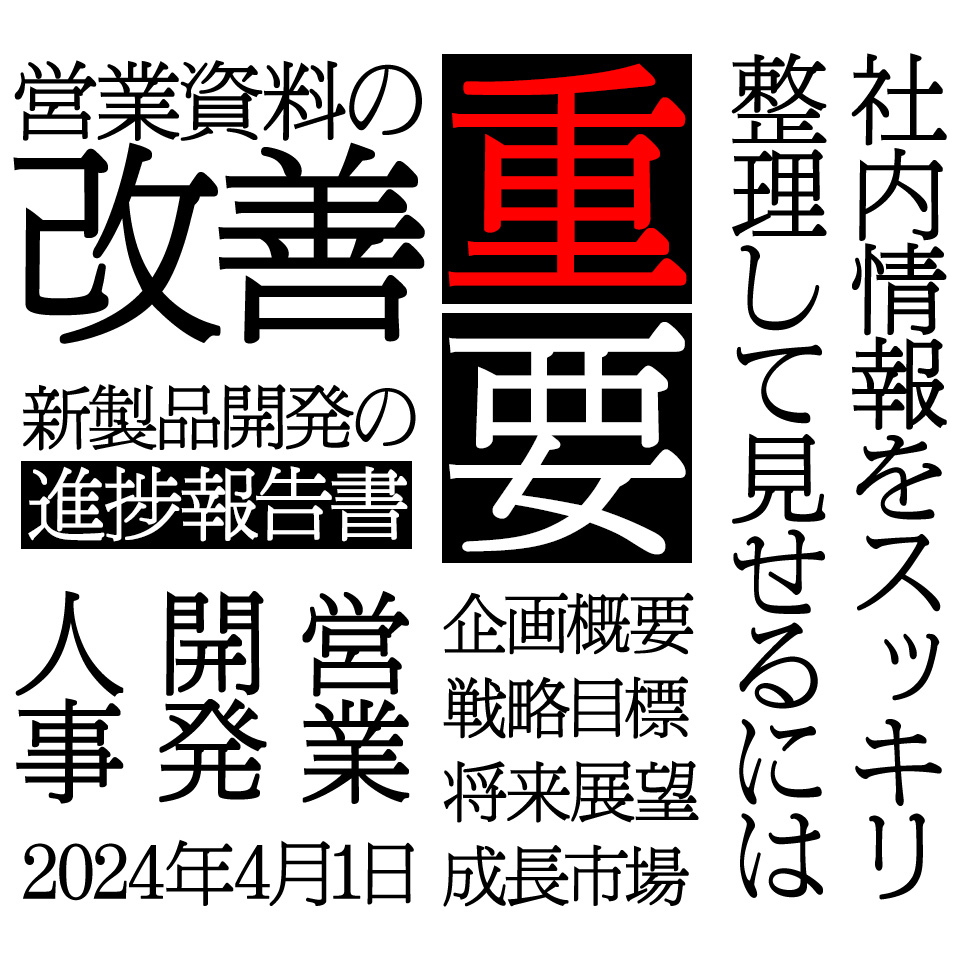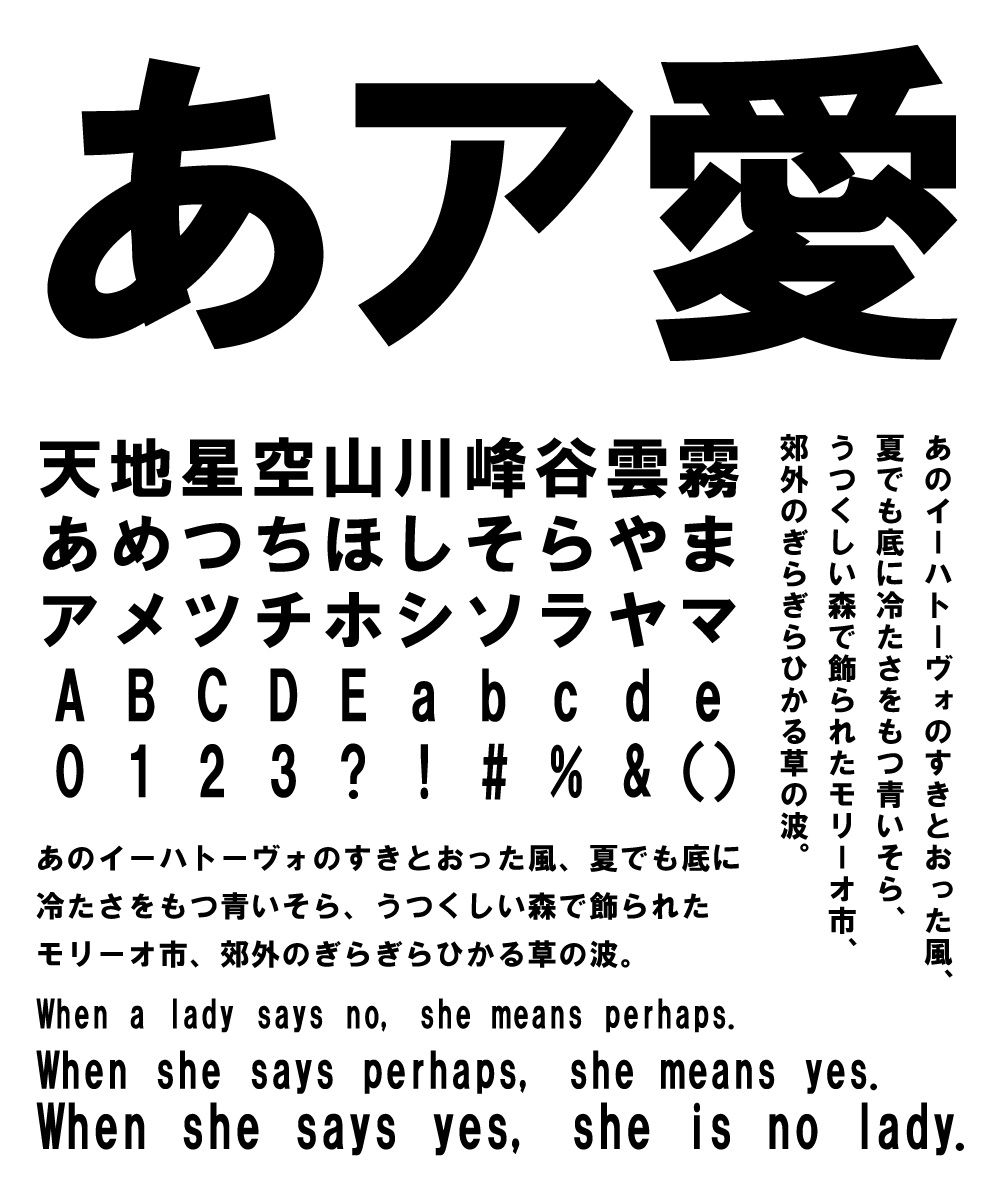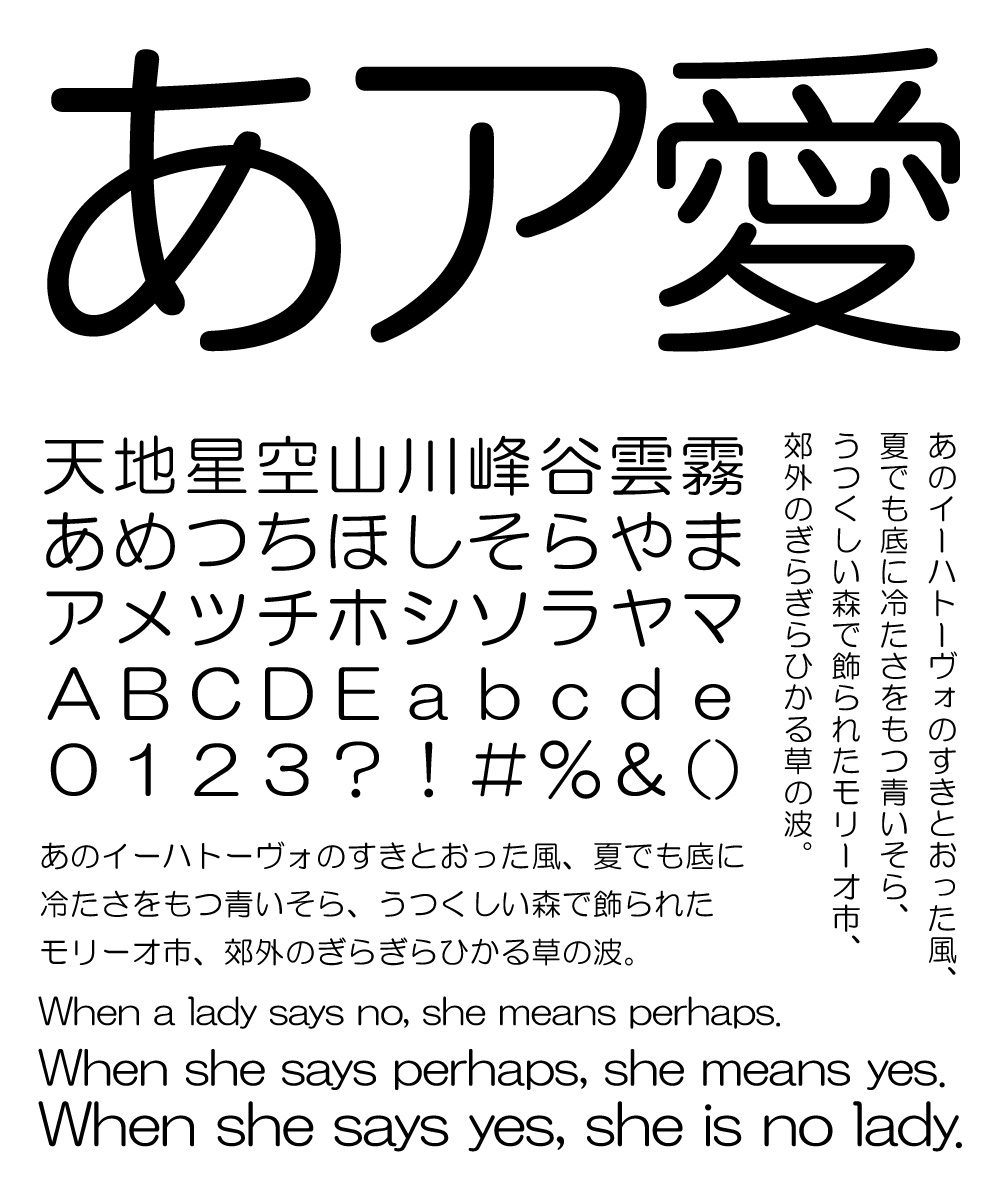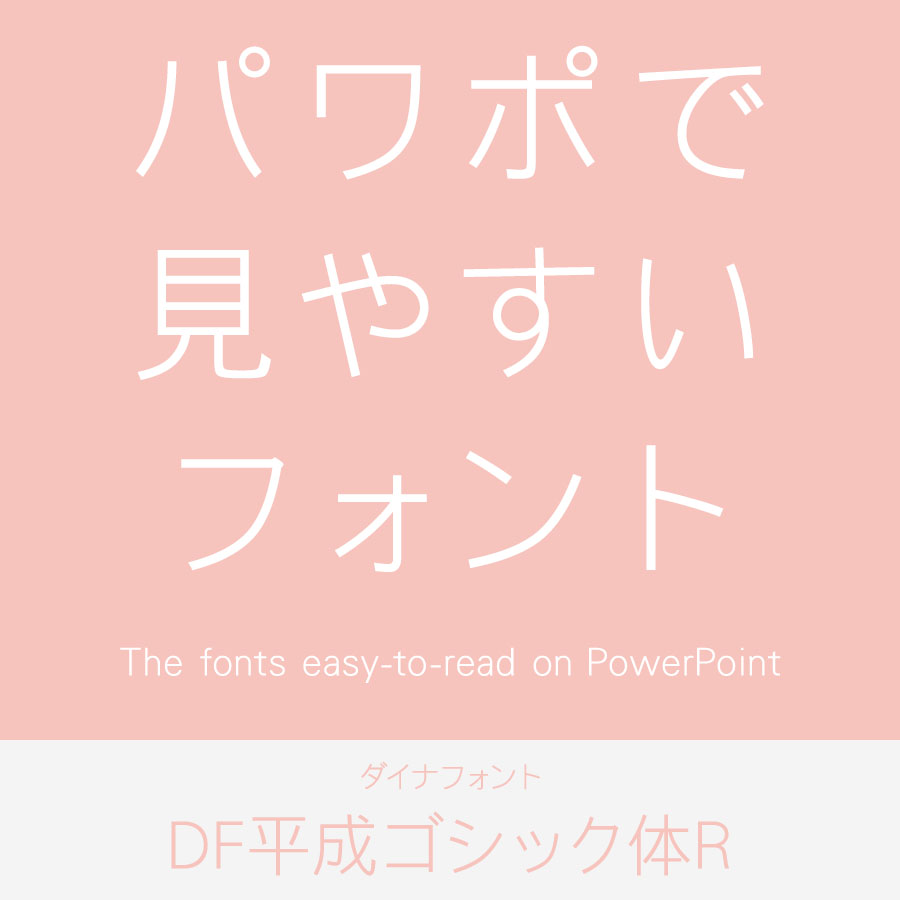
プレゼン資料の成功は、視覚的な要素に大きく影響されます。特に本文のフォント選びは、情報の伝達効率と読者の印象に直結します。明朝体、ゴシック体、毛筆書体、手書きフォントの四つのフォントタイプを取り上げ、それぞれの特性や適用場面、メリット、デメリットを解説し、最適なフォント選びなどをご紹介します。
パワーポイントのフォント選びの5つのポイント
プレゼン資料に適したフォントを選ぶ際に考慮すべきポイントは次の5つです。
① 視認性
視認性は、フォントがどれだけ目立つか、または視覚的にどれだけ鮮明かを示します。視認性が高いフォントは、視覚的に強く、一目で理解できます。
② 可読性
可読性は、テキストがどれだけ読みやすいかを示します。可読性が高いフォントは、長時間の読み物に適しています。
③ 判読性
判読性は、文字や単語がどれだけ明確に識別できるかを示します。判読性が高いフォントは、小さなサイズでもはっきりと読むことができます。
④ 互換性
互換性は、フォントがさまざまなデバイスやオペレーティングシステムでどれだけ一貫性を保つかを示します。互換性が高いフォントは、どのデバイスでも同じように表示されます。
⑤ 太字にも対応しているか
太字のフォントは、強調したい部分に使用します。しかし、すべてのフォントが太字に対応しているわけではありません。そのため、太字を使用する予定がある場合は、太字に対応しているフォントを選ぶことが重要です。
フォントの変更だけで印象が大きく変わる
フォントの選択は、文章やプレゼンテーションの印象を根本から変える力を持っています。この記事では、フォントが視覚的なコミュニケーションにどれほど影響を与えるかを詳しく解説し、適切なフォントを選ぶための具体的なアドバイスと例を紹介します。フォントの微妙な違いが持つ意味と重要性を探ります。
パターン1:保育園・幼稚園の「おたより」編
パターン2:社内での「会議プレゼンテーション」編
プレゼンテーションは、その資料の第一印象が成功の鍵を握る場合が多いです。表紙は特に重要で、使用するフォントによって、受け手の印象が大きく変わることがあります。ここでは、プレゼン資料の表紙に適したフォントの種類を紹介し、それぞれのフォントが視聴者に与える印象やメリット、デメリットを掘り下げます。
タイプフェイス別 表紙イメージ
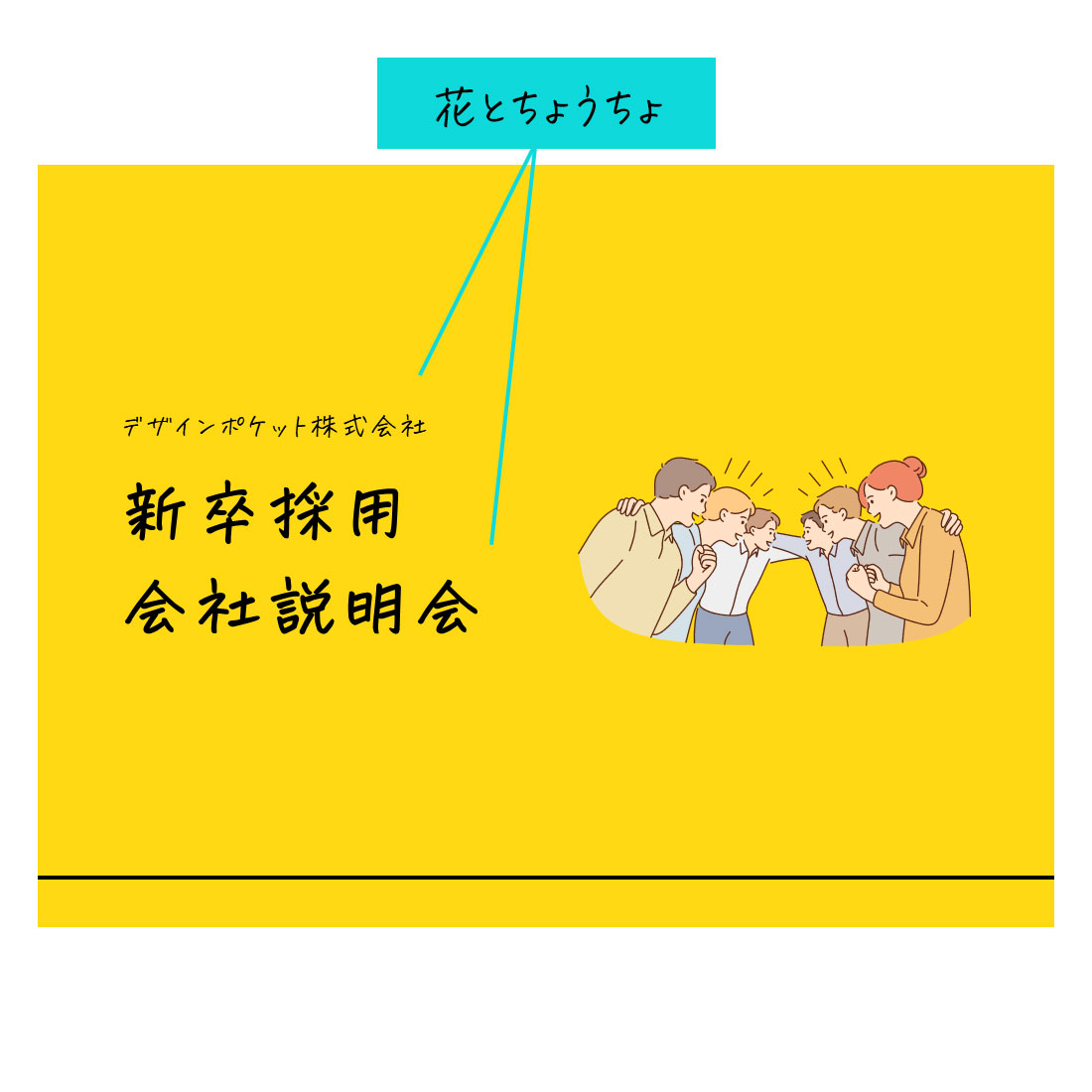
明朝体:伝統と信頼の象徴
明朝体は、その繊細なラインと伝統的な美しさで、フォーマルな印象を与えるフォントです。表紙に明朝体を使用することで、内容の正確性や信頼性を強調し、学術的または歴史的なテーマに最適です。
ゴシック体:クリアで現代的な感覚
ゴシック体は、そのクリアでモダンな外観が、特にビジネスやテクノロジー関連のプレゼンに適しています。表紙にゴシック体を使用することで、シャープでプロフェッショナルな印象を与えることができます。
毛筆書体:芸術性と感情の表現
毛筆書体は、感情豊かな表現が可能で、特に文化的または芸術的なテーマのプレゼンにマッチします。このタイプのフォントは、視聴者に強い印象を与え、情緒的なつながりを生み出すことができます。
手書き書体:カジュアルで親しみやすい
手書きフォントは、カジュアルで親しみやすい印象を与え、非公式な会議や創造的なプレゼンに適しています。この種のフォントは、個性を出しやすく、リラックスした雰囲気を作り出すことができます。
明朝体 | ・伝統的な印象で、内容の信頼性を高める ・フォーマルなプレゼンに適している |
・クリエイティブなテーマにはあまり向かない ・若い観衆には堅苦しく感じられる可能性 |
ゴシック体 | ・現代的で洗練された印象 ・視認性が高く、情報がはっきりと伝わる |
・個性を強く出すのが難しい ・過度にシンプルになりがちで印象に残りにくい |
毛筆書体 | ・強い個性と芸術的な印象を表現 ・情緒的なコネクションを促進 |
・視認性が低くなることがある ・フォーマルな設定には不向き |
手書き書体 | ・親しみやすくカジュアルな印象 ・創造性と個性を強調 |
・プロフェッショナルな印象に欠ける場合がある |
タイプフェイス別 本文
プレゼン資料の本文用フォントは、情報の伝達効率と視覚的魅力のバランスを考える必要があります。
明朝体:細部まで繊細に
明朝体は、細かい部分が特徴的で、読みやすさとフォーマル感を提供します。本文に使うことで、伝統的かつ権威のある印象を与え、特に文書や学術的な内容に適しています。
ゴシック体:現代的でクリーン
ゴシック体は明確で読みやすく、現代的なデザインに最適です。ビジネスや技術的なプレゼン資料の本文に使用することで、プロフェッショナルで洗練された印象を与えます。
毛筆書体:情緒的で芸術的
毛筆書体は、感情的なニュアンスを表現でき、文化的またはアート関連のプレゼンに適しています。ただし、本文全体に使用すると読みづらくなることがあるため、使用する際は工夫が必要です。
手書きフォント:個性的でフレンドリー
手書きフォントは、カジュアルでフレンドリーな印象を与え、創造的なプレゼンに最適です。ただし、プロフェッショナルな環境では適さない場合があります。
明朝体 | ・高い読みやすさ ・伝統的で信頼性のある印象 |
・クリエイティブな内容には少々堅苦しい ・モダンなデザインとは馴染みにくい場合がある |
ゴシック体 | ・視認性が高い ・現代的でスタイリッシュな見た目 |
・表現の幅が限られることがある ・暖かみや柔らかさを欠くことがある |
毛筆書体 | ・個性的で感情的な表現が可能 ・芸術的なデザインにマッチ |
・一般的な読みやすさに欠ける ・フォーマルな環境には不適切 |
手書き書体 | ・創造性を強調しやすい ・親しみやすい印象を与える |
・プロフェッショナルな印象に欠ける場合がある ・一部の観客には不適切と感じられることがある |
プレゼンを作る時に最適なタイプフェイスとは
プレゼン資料を作成する際には、各部分に適したフォントの選択が重要です。以下に、タイトル、見出し、本文それぞれに適したフォントの種類をご紹介します。
タイトルに最適なタイプフェイスは、ゴシック体 or デザイン・手書き書体
タイトルはプレゼンテーションの主題を伝え、視聴者の注意を引く必要があるので、ゴシック体が適しています。ゴシック体は太い線やシンプルな形状が特徴で、強い印象を与えます。ゴシック体以外にも、大胆で視覚的に魅力的なデザイン書体や手書き書体も適しています。ただし、可読性を確保するためには、複雑すぎないデザインを選ぶことが重要なポイントです。
見出しに最適なタイプフェイスは、明朝体 or ゴシック体 or デザイン・手書き書体
見出しは文章の区切りや重要なポイントを示すため、明朝体やゴシック体が適しています。明朝体は伝統的で格式のある印象を与えますが、ゴシック体は現代的でシンプルな印象を与えます。使用するフォントは、プレゼンのテーマや目的によって選択します。
本文に最適なタイプフェイスは、明朝体 or ゴシック体
本文は読みやすさが重要なので、明朝体やゴシック体が適しています。明朝体は日本語に親しみやすく、伝統的な印象を与えます。一方、ゴシック体はシンプルでモダンな印象を与えます。本文のフォントは、読み手のニーズや文書のテーマに合わせて選択します。
2種類から3種類のフォントを使用すると綺麗な仕上がりに!
パワーポイントでプレゼンテーション資料を作成する際のフォント選択については、特定の制限数はありません。しかし、デザインの観点から言えば、一般的には2種類から3種類のフォントを使用することが推奨されます。
これは視覚的な一貫性を保つためで、多くのフォントを使用すると視覚的な混乱を引き起こし、メッセージの伝達を困難にする可能性があります。一方、フォントが1種類だけでは、強調したいポイントを視覚的に区別するのが難しくなるかもしれませんので、最大のフォント数は3種類が一般的なガイドラインとなります。
2種類から3種類のフォントを使ってみました。
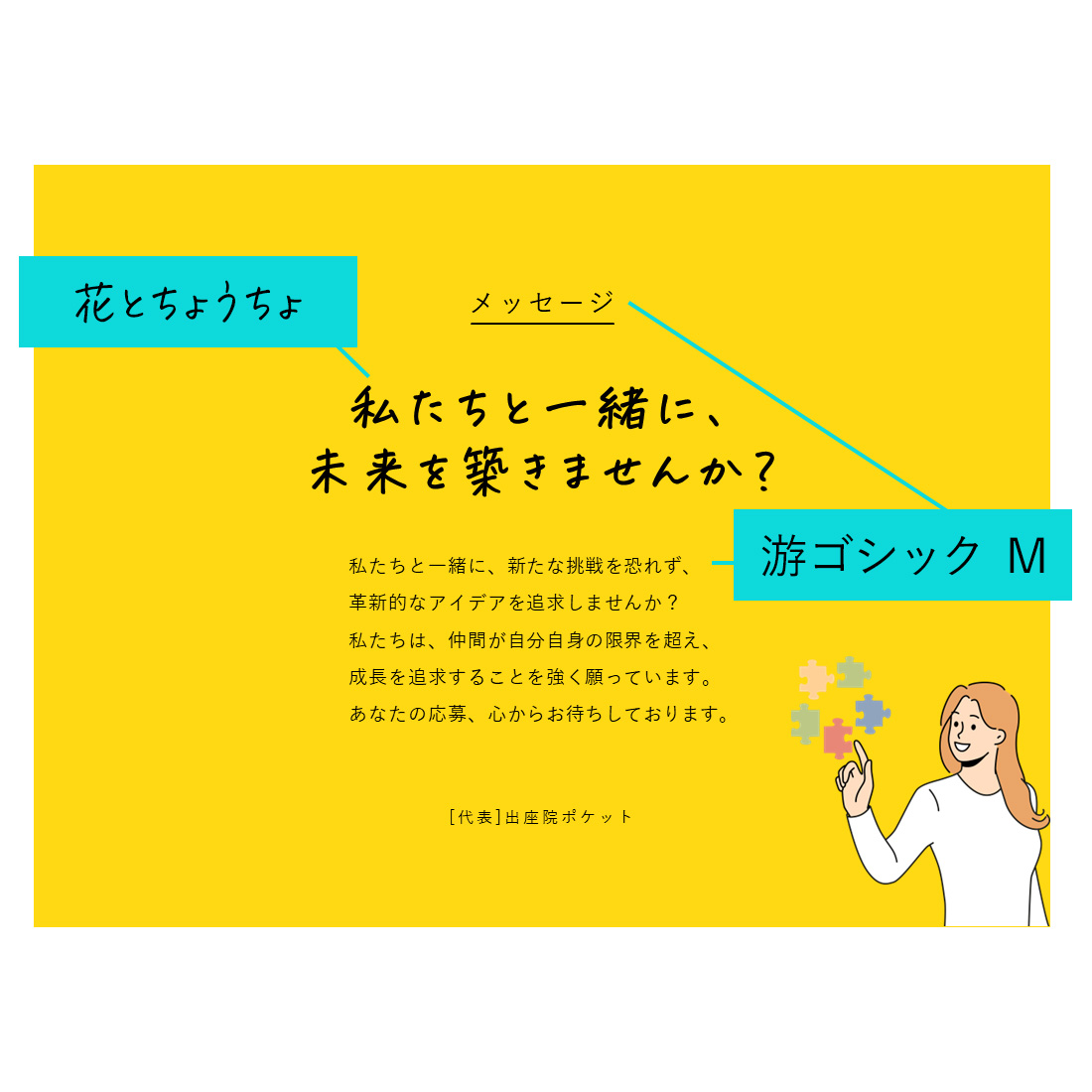
タイトル:ゴシック体
ゴシック体をプレゼン資料のタイトルに使用することで、視認性やデザインの一貫性、読みやすさが向上し、全体的にモダンで洗練された印象を与えることができます。
見出し:手書き書体・ゴシック体
プレゼン資料の見出しにゴシック体を使用すると、モダンで洗練された印象を与え、視認性が高くプロフェッショナルな雰囲気を醸し出します。また、見出しに手書きフォントを使用すると、親しみやすさと温かみを感じさせ、他の形式的な資料との差別化を図ることができます。
本文:明朝体
プレゼン資料の本文に明朝体を使用すると、伝統的で上品な印象を与え、文字の可読性が高くなるため、長文が読みやすくなります。